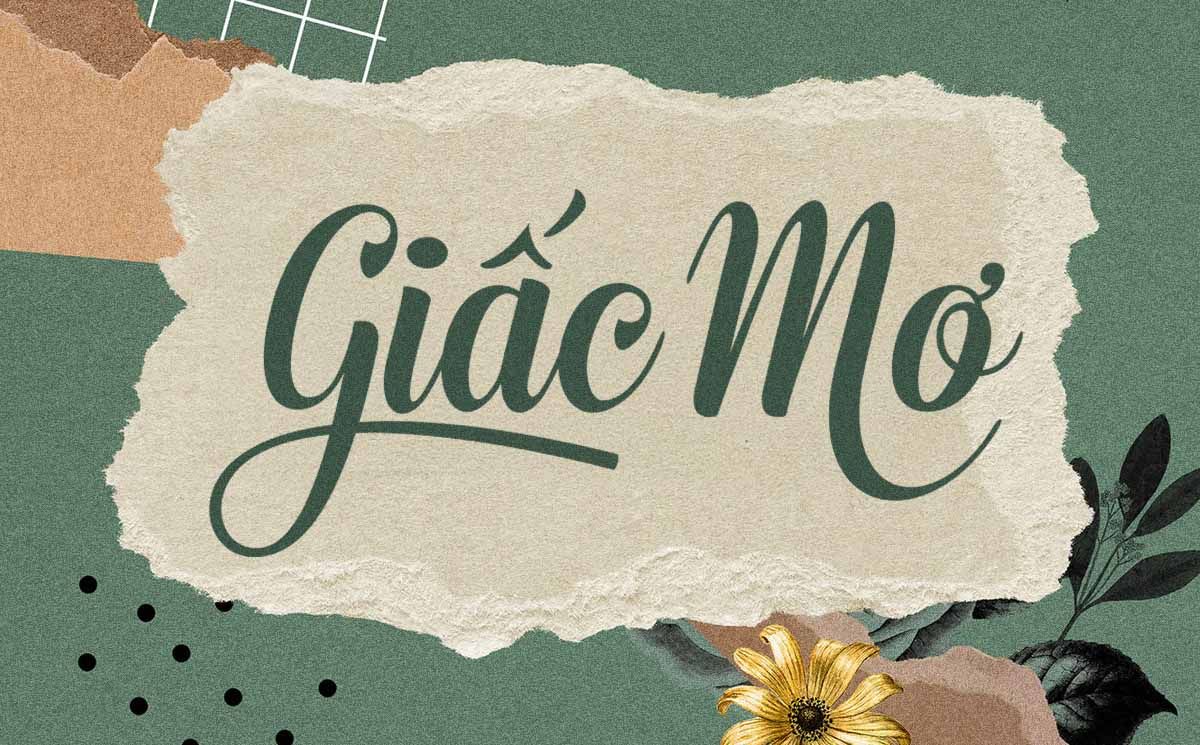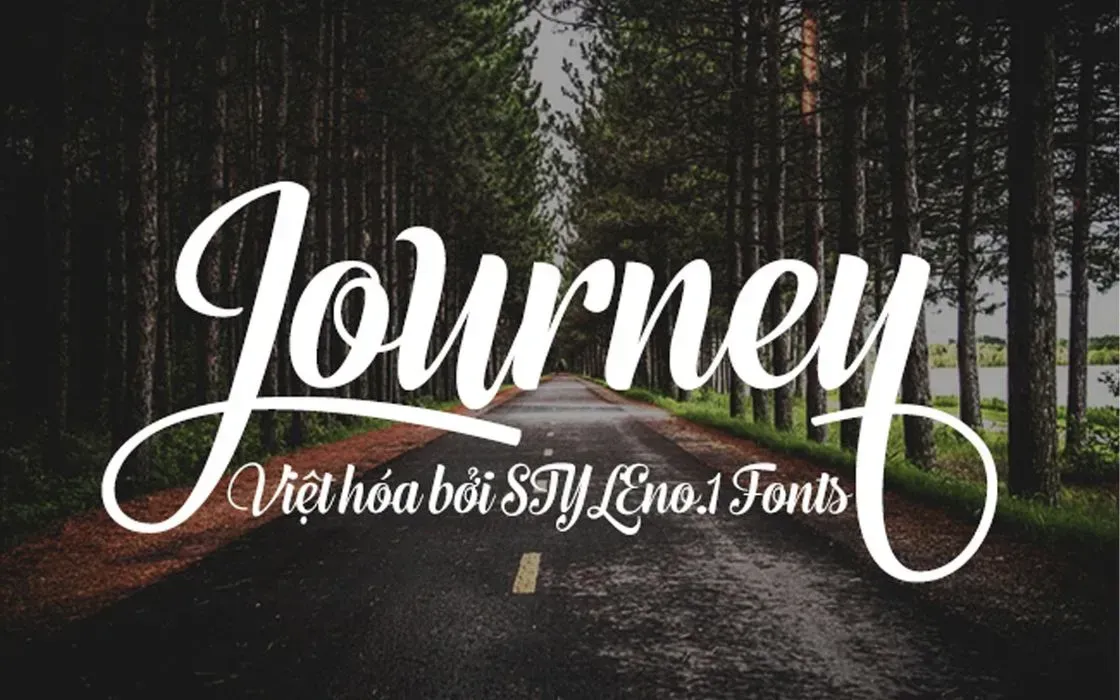
SVN Journey là một kiểu font script viết tay mang phong cách tự nhiên, mềm mại và nghệ thuật, mô phỏng những nét chữ tay uyển chuyển như đang lướt nhẹ trên trang giấy. Font nổi bật với các nét cong duyên dáng, kết nối linh hoạt giữa các ký tự, tạo cảm giác gần gũi, lãng mạn và đầy cảm xúc cá nhân.
Từng chữ cái trong Journey được thiết kế với độ nghiêng nhẹ, thanh đậm linh hoạt và nhịp điệu thị giác mượt mà, rất phù hợp cho các thiết kế cần thể hiện sự tinh tế, nhẹ nhàng và mang tính cá nhân hóa cao.
– Thiệp cưới, thư tay, thiệp cảm ơn
– Logo thương hiệu mỹ phẩm, thời trang nữ, quà tặng
– Tiêu đề blog cá nhân, bìa sách nghệ thuật, tạp chí lifestyle
– Bao bì sản phẩm handmade hoặc phong cách vintage
Font gốc Journey Script được thiết kế bởi Nicky Laatz, một nhà thiết kế nổi tiếng với những bộ font viết tay đầy cảm xúc, luôn gợi được sự kết nối giữa chữ viết và cảm giác thủ công – con người.
Phiên bản Việt hóa bởi nhóm SVN Fonts đã được bổ sung đầy đủ dấu tiếng Việt, giữ nguyên vẻ bay bổng và mềm mại của bản gốc, đồng thời đảm bảo font hoạt động mượt mà trên các phần mềm như Illustrator, Photoshop, Canva, Word…
Nếu bạn đang tìm kiếm một font viết tay mềm mại, tự nhiên và đầy chất thơ, thì SVN Journey chính là lựa chọn lý tưởng để truyền tải cảm xúc chân thành, vẻ đẹp tinh tế và tính nghệ thuật cá nhân trong từng thiết kế.